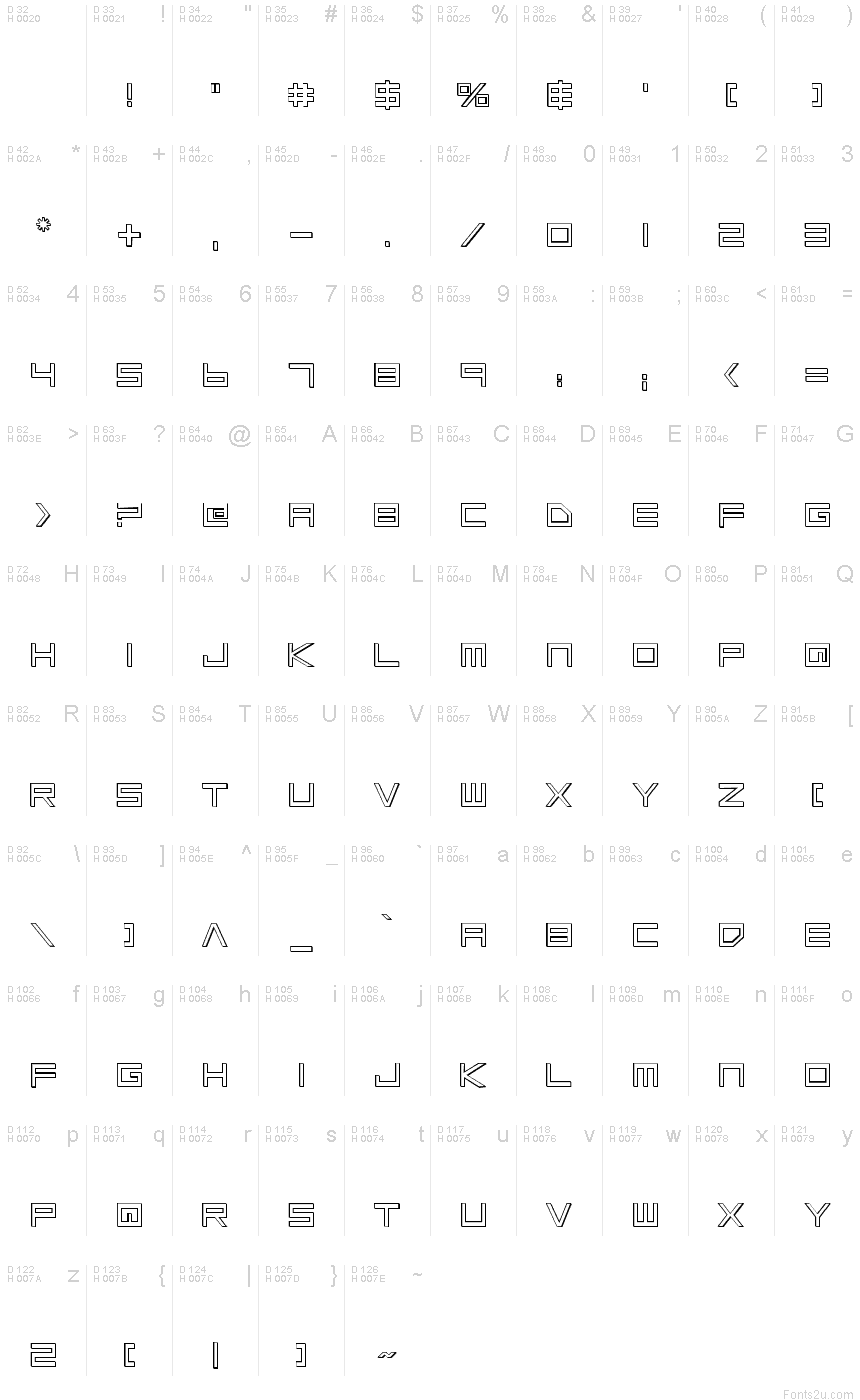
Low Gun Screen Outline, di Iconian Fonts, è un font 3D gratuito in stile techno (solo maiuscole) ispirato alla geometria quadrata delle interfacce arcade. Le lettere ampie e contornate, con angoli decisi e spazi aperti, creano un ritmo che ricorda i circuiti stampati, impreziosito da un sottile effetto 3D.
La sua struttura cava conferisce un aspetto leggero e tecnico ai loghi di gioco e al branding e-sport, senza mai perdere il suo carattere digitale. Utilizza questo font gratuito per titoli sci-fi, artwork di musica elettronica, interfacce grafiche o poster futuristici: le sue linee angolari continue richiamano perfettamente schermi, circuiti e strutture tecniche.